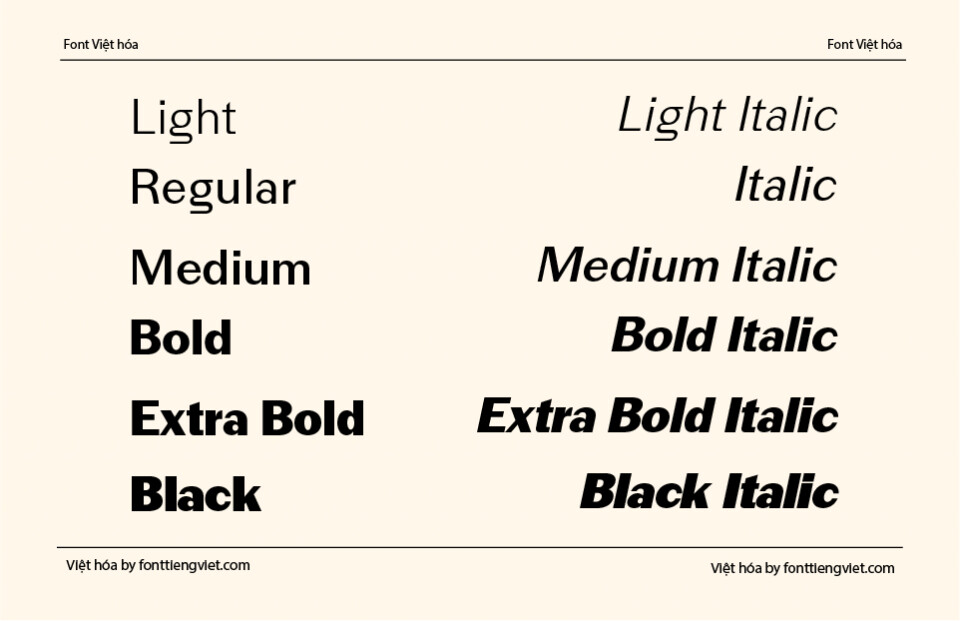
Font việt hóa Picaresk Bold đẹp dành cho thiết kế
Picaresk Bold là một kiểu display font (font tiêu đề) ấn tượng, thuộc dòng chữ cổ điển pha hiện đại, mang hơi hướng của các áp phích, tạp chí và biển quảng cáo thế kỷ 20. Với thiết kế đậm nét, mạnh mẽ và phong cách rất riêng, font này dễ dàng thu hút ánh nhìn và để lại dấu ấn thị giác sâu sắc.
Đặc điểm nổi bật của Font Picaresk Bold
• Nét chữ dày, táo bạo: Đúng như tên gọi “Bold”, font sở hữu độ đậm mạnh mẽ, rất phù hợp cho các tiêu đề, poster và thiết kế cần tạo điểm nhấn.
• Chữ in hoa đồng đều, hình khối rõ ràng: Mỗi ký tự đều được thiết kế sắc nét với cấu trúc hình học rõ rệt, giúp dễ đọc và dễ nhận diện.
• Phong cách vintage – retro hiện đại: Kết hợp giữa sự cổ điển của typography thời kỳ đầu với xu hướng tối giản hiện đại.
• Độ tương phản cao, dễ đọc: Ngay cả ở kích thước lớn hoặc nhỏ, Picaresk Bold vẫn giữ được khả năng truyền tải rõ ràng.
• Hỗ trợ tiếng Việt: Font đã được Việt hóa hoàn chỉnh, tương thích đầy đủ với dấu tiếng Việt.
Ứng dụng của Font Picaresk Bold
Picaresk Bold là lựa chọn lý tưởng cho các dự án thiết kế cần sự chuyên nghiệp, cổ điển nhưng không kém phần nổi bật:
• Thiết kế poster, tiêu đề sách, bìa tạp chí: Đặc biệt hợp với các chủ đề về văn hóa, nghệ thuật hoặc retro.
• Logo và thương hiệu cá tính: Tạo nên hình ảnh thương hiệu mạnh mẽ, tin cậy và có chiều sâu lịch sử.
• Bao bì sản phẩm thủ công, sản phẩm truyền thống: Gợi nhớ đến sự hoài cổ, sang trọng và chất lượng cao.
• Ấn phẩm quảng cáo hoặc banner sự kiện: Tạo điểm nhấn thị giác và sự chuyên nghiệp trong truyền thông.
Picaresk Bold là một font chữ hiển thị mạnh mẽ, cá tính và đậm chất hoài cổ. Dù bạn đang thiết kế poster nghệ thuật, logo mang hơi hướng vintage hay các ấn phẩm cần gây ấn tượng mạnh mẽ, Picaresk Bold chắc chắn là một công cụ đắc lực không thể thiếu trong bộ font của bạn.